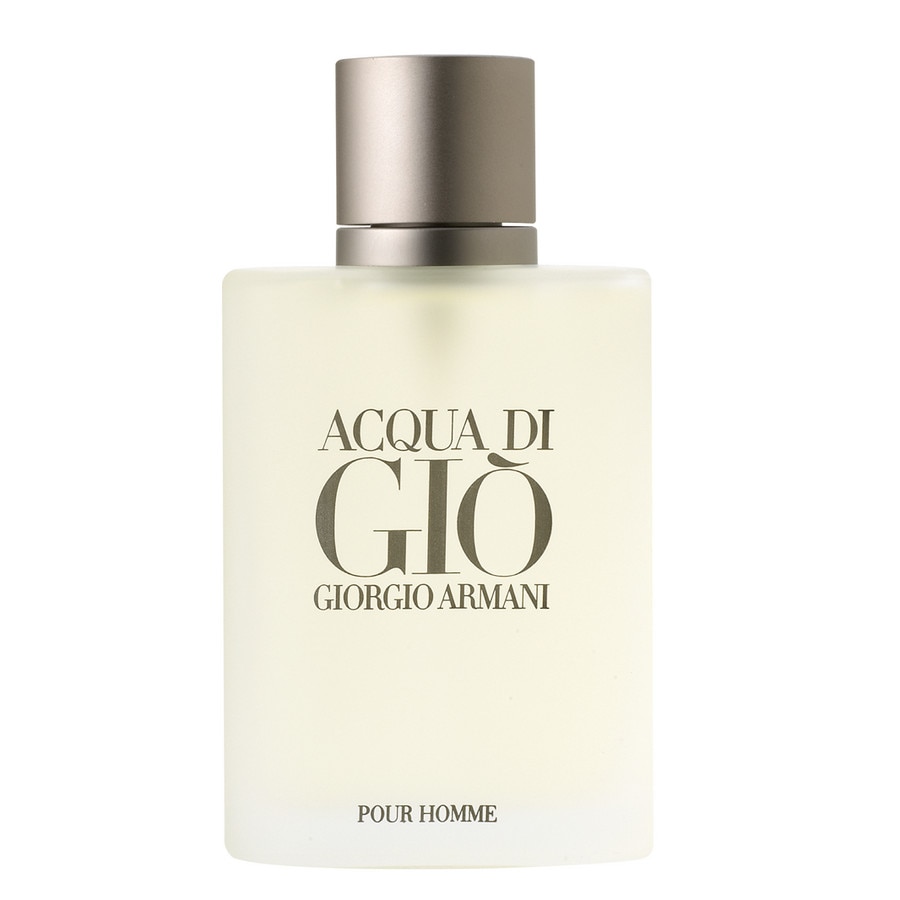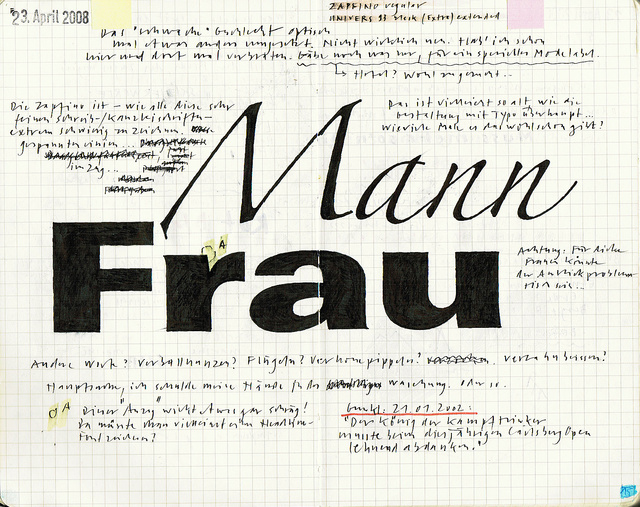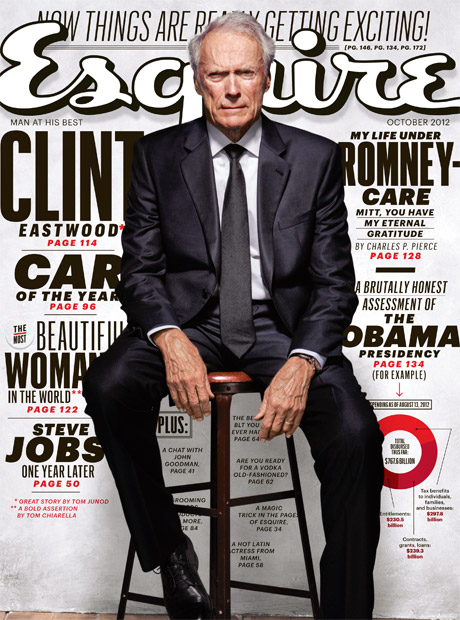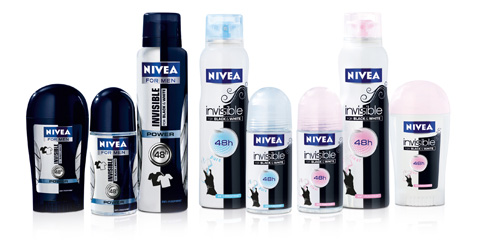
„weibliche“ Schriften auf „Männerprodukten“ und umgekehrt?
ich stecke momentan mitten in der Recherchephase für mein Diplomthema und könnte eure Mithilfe gebrauchen.
Es geht darum:
Schriften werden zum Teil mit den Attributen „männlich“ oder „weiblich“ versehen. (Inwiefern das politisch korrekt oder Erziehungs-/Erfahrungssache ist, wurde schon mehrfach diskutiert und das möchte ich hier bitte außen vor lassen…)
Jedenfalls wird mir wohl kaum jemand widersprechen, wenn ich behaupte, dass weiche, runde, fließende und auch kontrastreiche Schriften eher als feminin und im Gegensatz dazu blockige, kantige, dunkle, kontrastarme Schriften eher als maskulin wahrgenommen werden.
Zu dieser Erkenntnis führte mich unter anderem die Analyse von Schriften auf Produkt(-verpackung)en bzw. Werbung mit geschlechtsspezifischen Zielgruppen.
Nun suche ich gerade allerdings nach den Ausnahmen zu diesen Regeln, und da wird es schon gleich viel schwieriger.
Könnt ihr mir Beispiele nennen, in denen die Schriftwahl genau umgekehrt wie oben beschrieben erfolgt ist? Ich meine hier zum Beispiel eine typische Frauenzeitschrift, bei der der Titel in einer fetten, kantigen Slab Serif gesetzt ist oder ein Männerparfum, das in leichten, weichen Schwungbuchstaben beschriftet ist.
Ich freue mich über alle Hinweise, gerne auch allgemein zum Thema :)
Die Mädchen-Ü-Eier sehen bis auf das rosa Häubchen genauso aus wie die früher Unisex- heute nur noch Jungs-Ü-Eier.
Habe jetzt nicht die Schriften im Kopf, aber das gesamte Marketing für Coke Zero ist darauf ausgerichtet, es als Coke Light für echte Männer zu präsentieren.
Der Bosch Ixo Vino hat eine weibliche Zielgruppe, die an ihre männliche Zielgruppe denkt (sehr verflochtenes Beziehungsspiel).
aber ich suche genau nach dem Gegenteil! Beispiele für „echte Männer-/Frauenprodukte“ gibt es ganz viele und die hab ich auch schon gesammelt und analysiert.
Was mir fehlt, sind eben „Männerprodukte“ mit „Frauenschriften“ und umgekehrt!
Vielleicht fallen da jemandem auch ein paar Sachen ein?
aber ich suche genau nach dem Gegenteil! Beispiele für „echte Männer-/Frauenprodukte“ gibt es ganz viele und die hab ich auch schon gesammelt und analysiert.
Was mir fehlt, sind eben „Männerprodukte“ mit „Frauenschriften“ und umgekehrt!
Vielleicht fallen da jemandem auch ein paar Sachen ein?
Ixo Vino und Ü-Ei sind doch Produkte gesuchter Sparte ;) Und sonst sehe ich Schwierigkeiten, da das Gender Mann bedrohter wahrgenommen wird als das Gender Frau. Bestenfalls kannst du in der LBGT-Szene da etwas finden, doch dann klappt die Gender-Falle gleich wieder zu...
die Ü-Eier sind zwar jetzt anscheinend für Jungs und Mädchen getrennt, jedoch ist das Jungs-Ei auch „männlich“ bzw. neutral und das Mädels-Ei eben „mädchenhaft“ gestaltet, auch was die Schriftwahl angeht.
Bei der Bosch-Ixo-Vino-Maschine ist es zwar nicht genauso, aber es ist dennoch nicht, was ich suche. Hier gibt es diesen Aufsatz, der für die Zielgruppe Frau gestaltet wurde und auch so vermarktet wird, aber ich würde trotzdem nicht sagen, dass sich hier Produkt und Schriftwahl widerspricht.
Ich habe jetzt eine Weile lang weitergesucht und endlich zwei Produkte gefunden, die halbwegs zu dem passen, was ich suchte:
Das Esquire-Männermagazin (ein „typisches“ Männermagazin, soweit ich das sehe), bei dem zumindest der Titel in einer „weiblich“ anmutenden, runden Schreibschrift gesetzt wurde:
und ein Frauenparfum, das zwar bzgl. Form und Farbe eher weiblich bzw. neutral gestaltet ist, aber die Schrift darauf doch eher kantig und demnach „männlich“:
Vielleicht kennt jemand noch mehr Produkte dieser Art?
Nivea verwendet eine richtig kräftige Schrift für die Frauenpflegeserien. Na gut, für die Männerpflegeserien auch … ;-)
Hallo Phoibos,
die Ü-Eier sind zwar jetzt anscheinend für Jungs und Mädchen getrennt, jedoch ist das Jungs-Ei auch „männlich“ bzw. neutral und das Mädels-Ei eben „mädchenhaft“ gestaltet, auch was die Schriftwahl angeht.
Meinem ungeschulten Auge nach sind die Schriften identisch (und das Design bis auf das rosa Häubchen auch).
Bei der Bosch-Ixo-Vino-Maschine ist es zwar nicht genauso, aber es ist dennoch nicht, was ich suche. Hier gibt es diesen Aufsatz, der für die Zielgruppe Frau gestaltet wurde und auch so vermarktet wird, aber ich würde trotzdem nicht sagen, dass sich hier Produkt und Schriftwahl widerspricht.
Ich meine nicht den Aufsatz (der peinlich genug ist), ich meine die Maschine als solche. Deren Zielgruppe sind Frauen, die Männern was "sinnvolles" schenken sollen, jedoch eigentlich für sich einen Flaschenöffner kaufen.
Das Esquire-Männermagazin (ein „typisches“ Männermagazin, soweit ich das sehe), bei dem zumindest der Titel in einer „weiblich“ anmutenden, runden Schreibschrift gesetzt wurde:
Irr und relevant trifft es doch ganz gut, hehe. Ich war jetzt in der Großansicht echt überrascht, dass die Buchstaben doch handgezeichnet sind! Sieht nach viel Fleiß aus!
Naja, nein, was wirklich Neues ist das natürlich nicht, aber interessant finde ich die Wirkung doch immer wieder… :-)